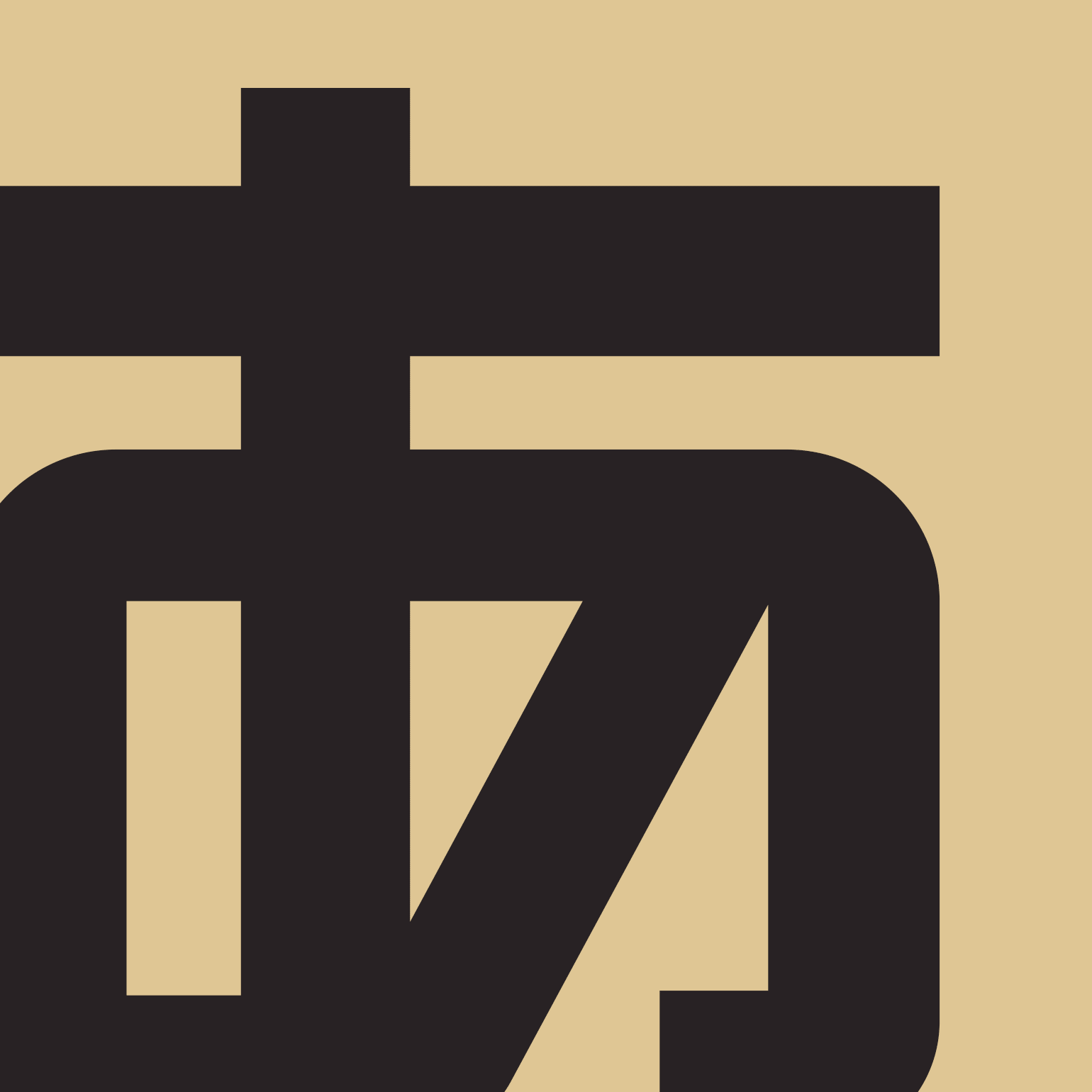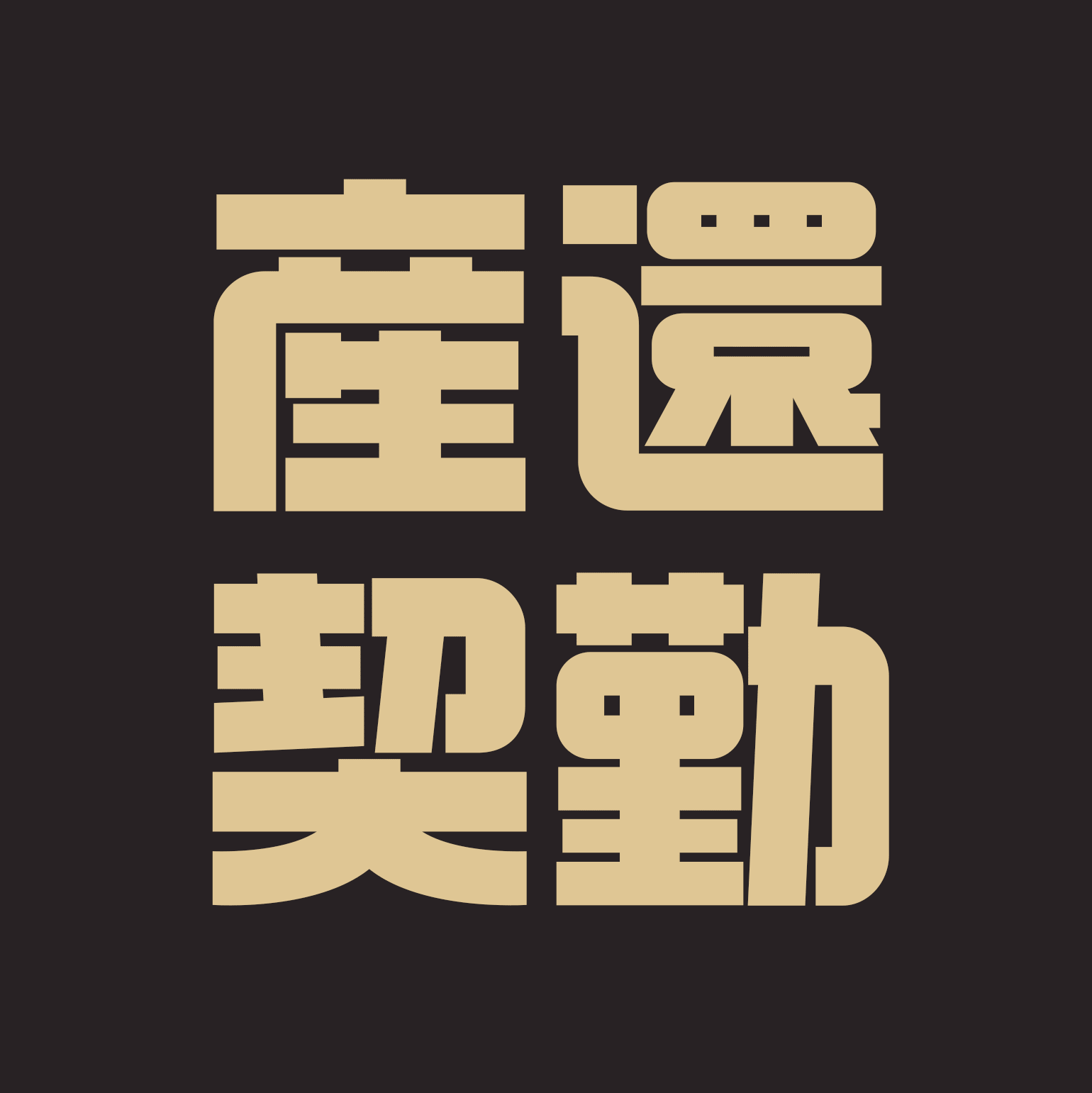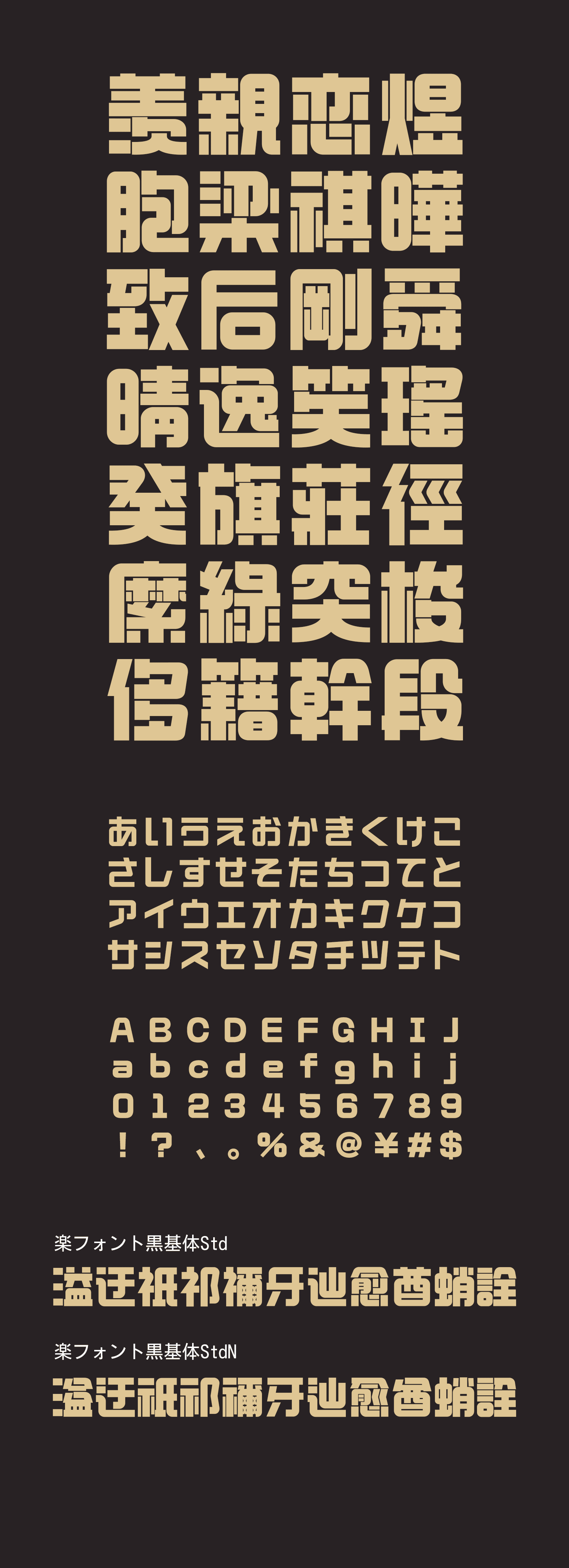
黒基体(こっきたい)
文字のふところを広く取り、安定感のある穏やかな雰囲気を演出。筆画の転換点には丸角を使っており、柔らかさとボリュームのあるゴシック体としての力強さを両立させています。その他、細部のデザインでは復雑な特徴をつけず、基本に戻った文字本来の素朴さと美しさを楽しめるような設計を施しています。